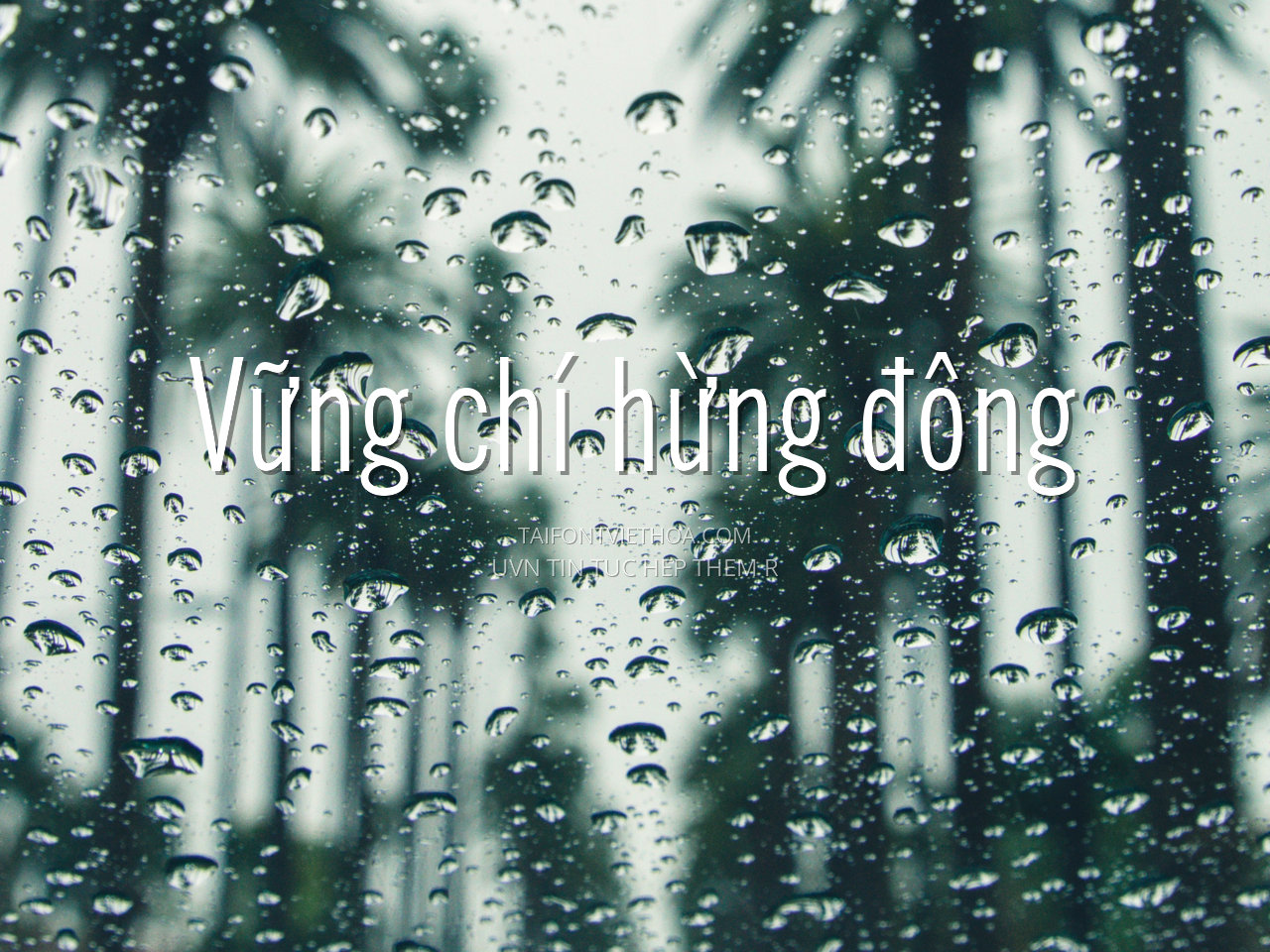
Font việt hóa UVN Tin Tuc Hep Them
Giới thiệu về font UVN Tin Tuc Hep Them
UVN Tin Tuc Hep Them là phiên bản được tinh chỉnh nâng cao từ dòng font UVN Tin Tuc Hep, với chiều ngang cực kỳ hẹp nhằm tiết kiệm tối đa diện tích trình bày mà vẫn đảm bảo độ rõ ràng khi hiển thị. Font này phù hợp cho những thiết kế cần tối ưu hóa không gian chữ, đặc biệt trong các ứng dụng báo chí, truyền hình, giao diện di động hoặc hệ thống điều hướng website. Được sưu tầm và chia sẻ bởi thành viên Font Chuẩn, UVN Tin Tuc Hep Them hiện được taifontviethoa.com sử dụng trong nhiều dự án thiết kế hiện đại, nơi hiệu quả thông tin và tính thẩm mỹ tối giản được ưu tiên hàng đầu.
Đặc điểm thiết kế và ứng dụng của UVN Tin Tuc Hep Them
UVN Tin Tuc Hep Them thuộc nhóm sans-serif với tỷ lệ ký tự hẹp, cấu trúc nét chắc chắn và độ dày đều, giúp font hiển thị tốt ở kích thước nhỏ và không gian hạn chế. Thiết kế này phù hợp cho tiêu đề, các khối văn bản cần truyền tải nhanh và rõ ràng trên giao diện hẹp như app di động, menu website hoặc giao diện dashboard. Font hỗ trợ tiếng Việt đầy đủ, đảm bảo tính ứng dụng rộng rãi trong thiết kế đa phương tiện.
Ứng dụng lý tưởng: thiết kế banner thông tin, app mobile, trình bày dữ liệu dashboard, hệ thống điều hướng UI, tiêu đề báo điện tử. Ngành nghề phù hợp: công nghệ, báo chí, giáo dục trực tuyến, marketing kỹ thuật số và thương mại điện tử.